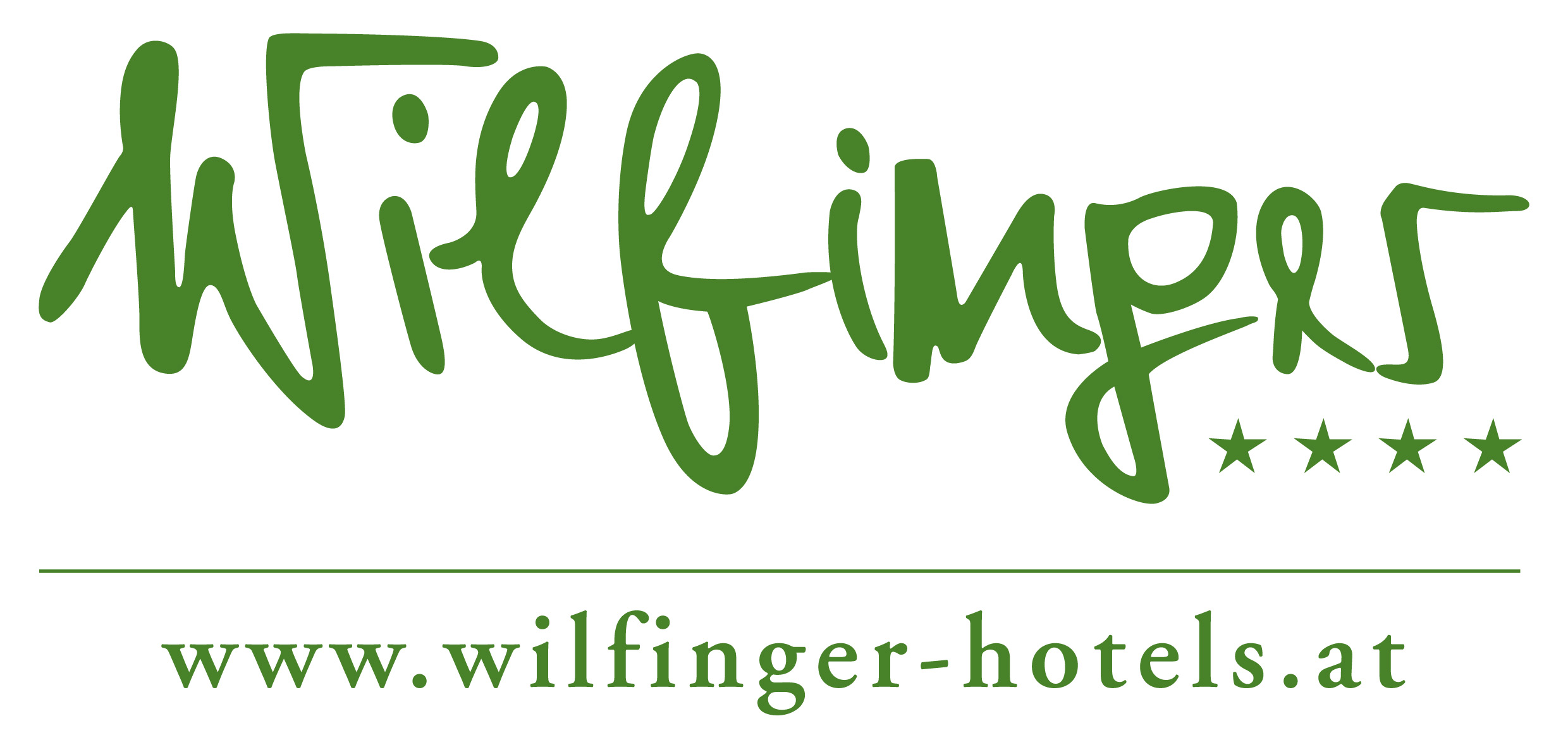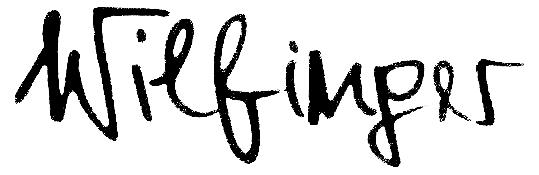
Welche Schrift ist das? Schreibschrift (vl umrandet?)
Hallo! Finde diese Schreibschrift leider nicht. habe einige ähnliche gefunden aber meistens passt das W bzw g nicht. Bitte um Hilfe!
Die beiden kleinen i sind doch sehr unterschiedlich. Ich gehe daher von handgezeichneten Buchstaben aus.
Auch der Rest des Logos ist so inkonsistent, dass ich von z.B. einer Unterschrift als Basis ausgehe – aus dieser entstand dann das Logo.